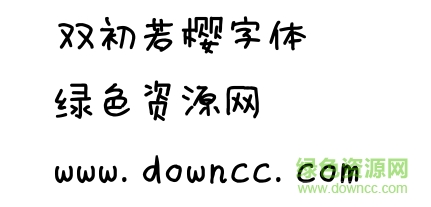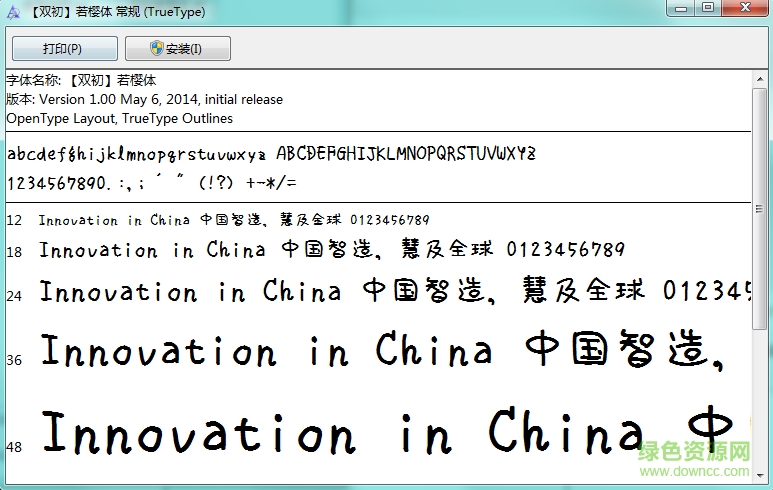
雙初若櫻體常規(guī)是一款字跡活潑可人的卡通字體,有著不規(guī)則的寫法,但整體更顯隨意不受拘束,充滿了童稚和浪漫之氣,喜歡的朋友就來綠色資源網(wǎng)下載吧!
若櫻體是可用于動(dòng)漫創(chuàng)作、名片設(shè)計(jì)、廣告創(chuàng)意等行業(yè)的一款藝術(shù)字體,字跡清雅,如同稚子的天真活潑,也像櫻花的浪漫和飄逸,別有一番視覺美感。